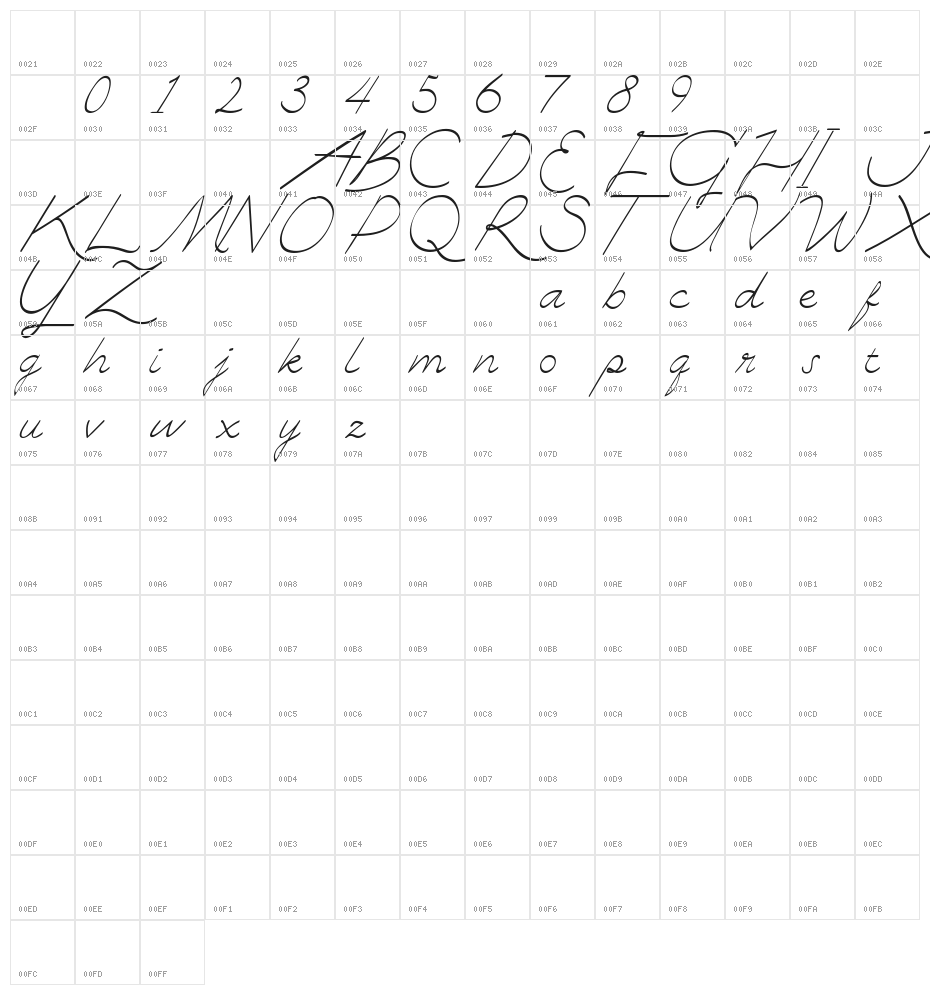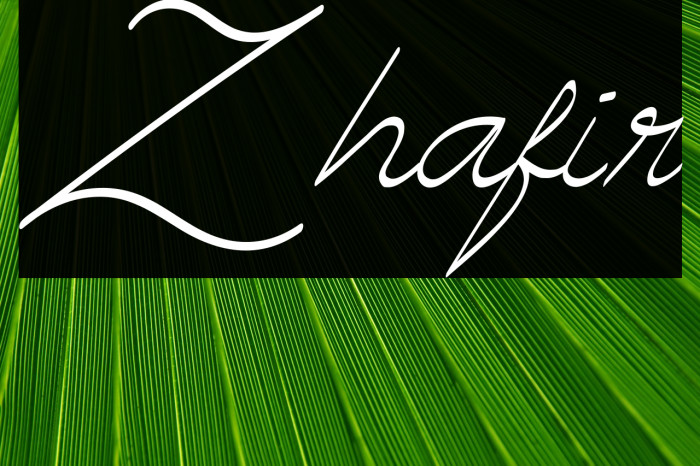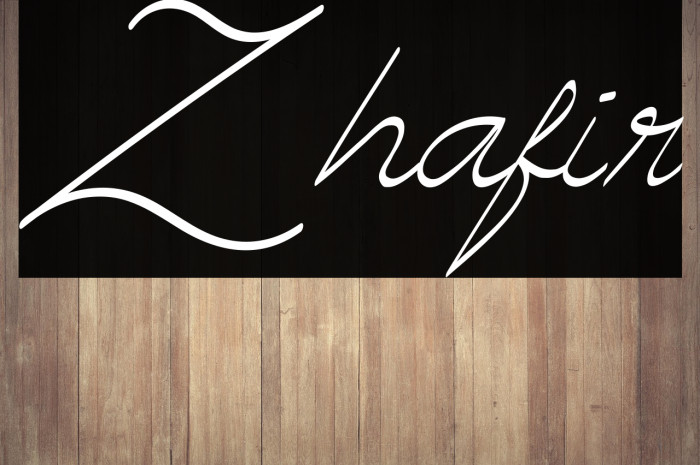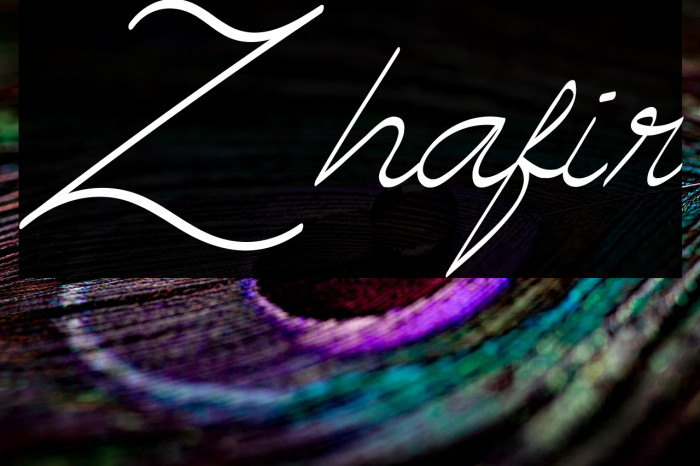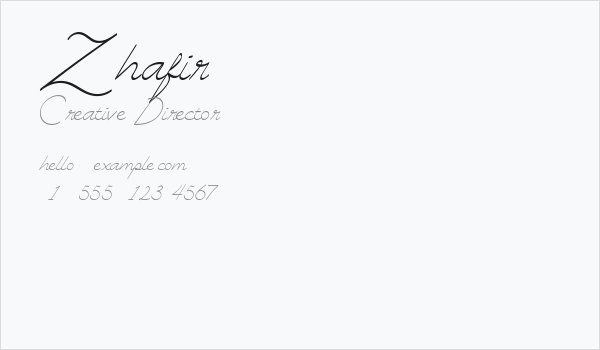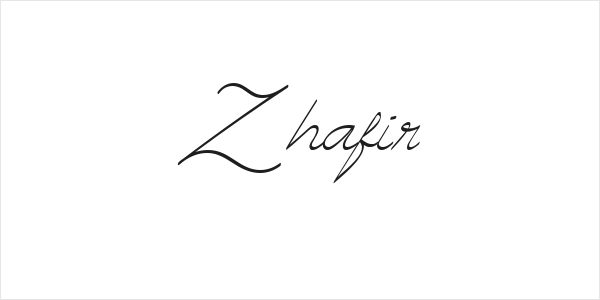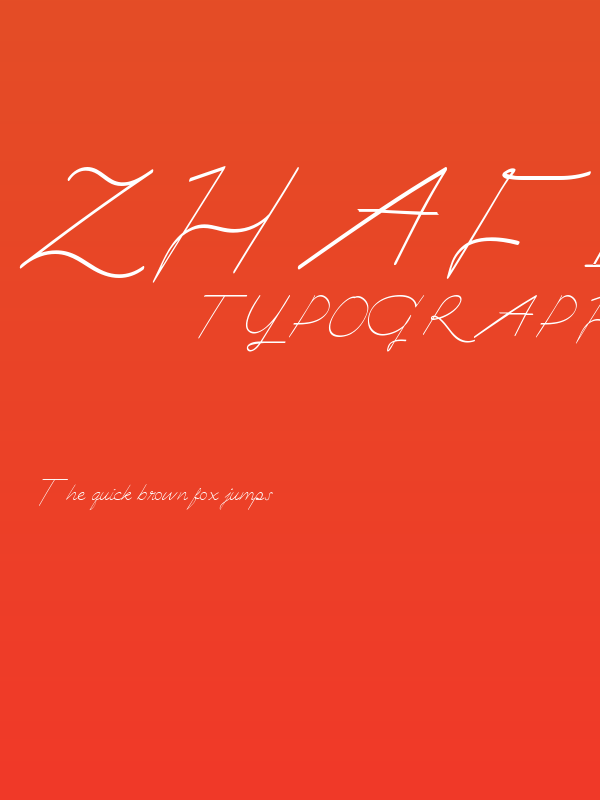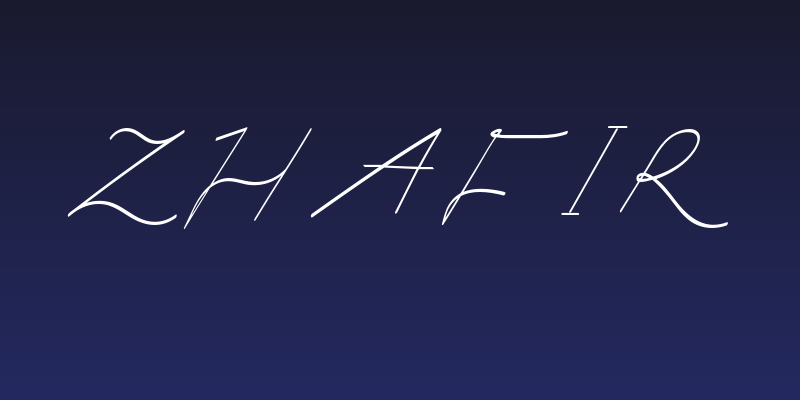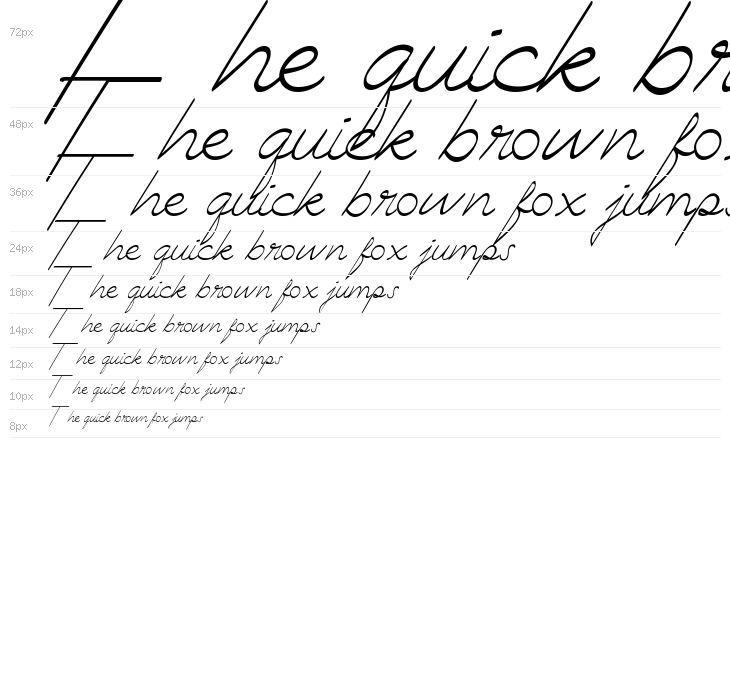
Zhafir Font
| Stile generale | Elegant, Handwritten |
| Caso d'uso | Logos, Invitations, Personal Branding |
| Progetti proposti | Ideal for wedding invitations, greeting cards, personal branding, and elegant packaging designs. |